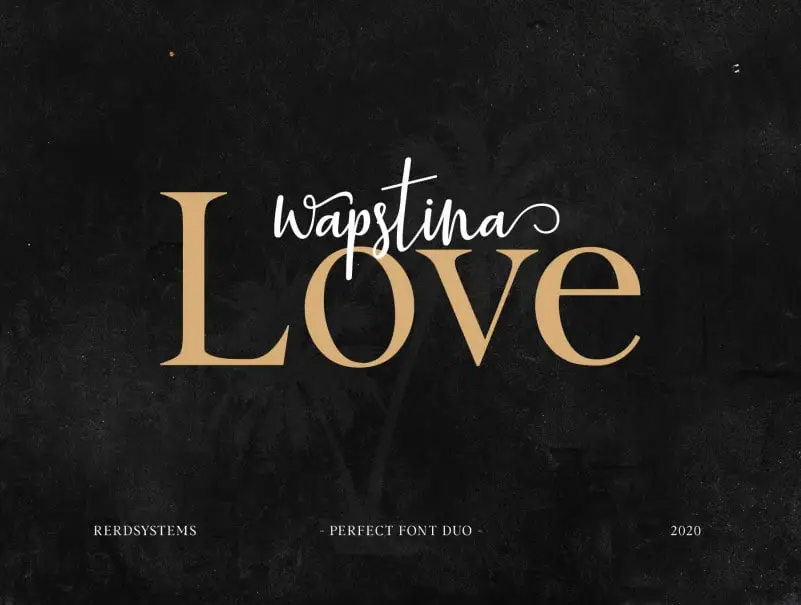
Wapstina Love – Duo Font – Download Grátis
A Wapstina Love Font Duo é uma combinação moderna entre uma tipografia elegante e serif clássica. Essa fonte única e incomum foi projetada para atender a um amplo espectro de aplicativos, desde blogs até cartões de casamento. Ela traz uma graça e sofisticação ao seu design, combinando os detalhes finos da tipografia serif com a elegância de uma escrita clássica. Ideal para uso em sua identidade visual digital como blog, logotipos, mídias sociais, publicações impressas, cartões de apelo e até mesmo cartão-maria-noite, a Wapstina Love Font Duo oferece um toque único que certamente destacará seu trabalho. Inspirada no estilo moderno da tipografia serifa, ela é uma opção perfeita para designers em busca de algo mais criativo para suas criações digitais.